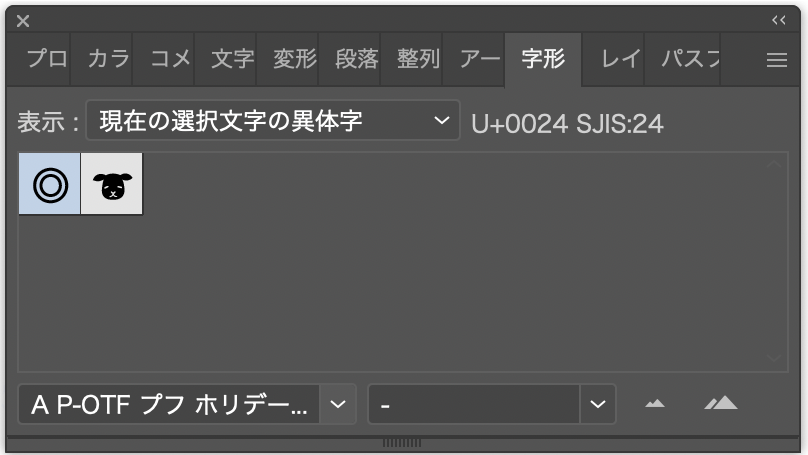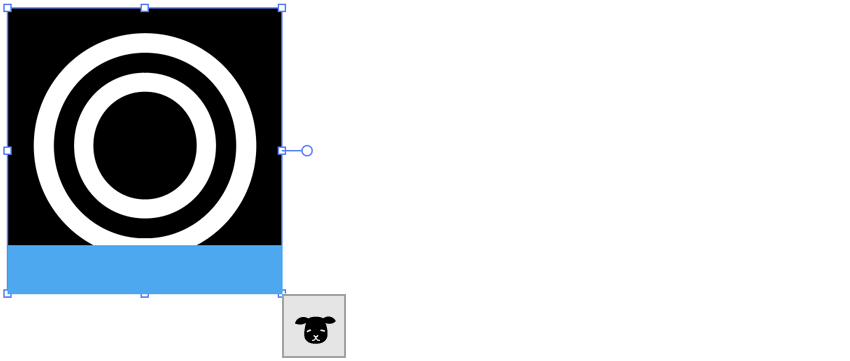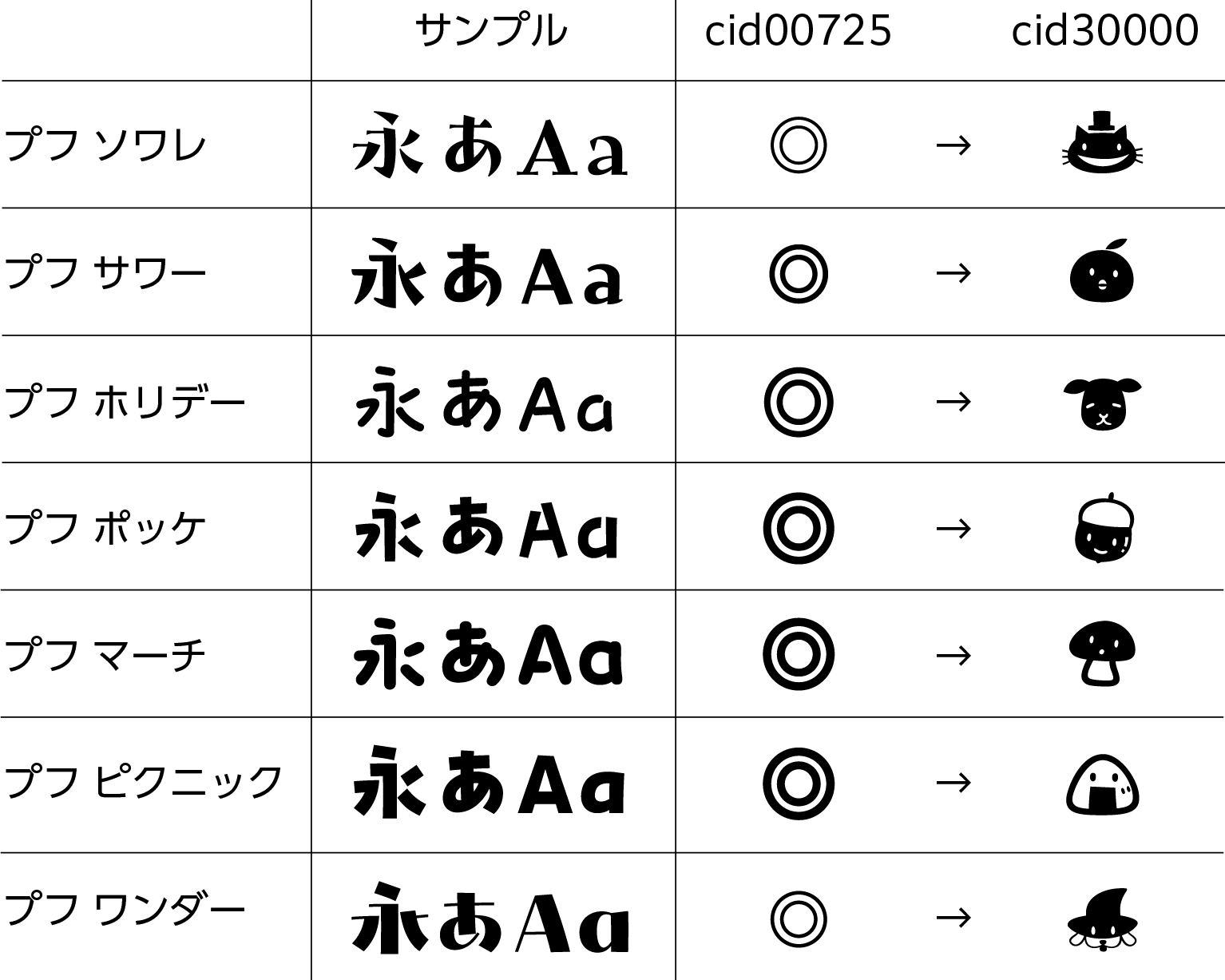
【「プフ」シリーズについて】
「プフ」シリーズは、統一しすぎない自由な字形と小さめの字面が特徴のデザイン書体ラインナップです。「プフ ソワレ」「フプ サワー」「プフ ホリデー」「プフ ポッケ」「プフ マーチ」「プフ ピクニック」「プフ ワンダー」の7書体が用意されています。
特徴の一つに、それぞれの書体のキャラクターを表すオリジナル絵文字を1文字搭載しており、「◎」に対応する異体字として選択入力が可能です。